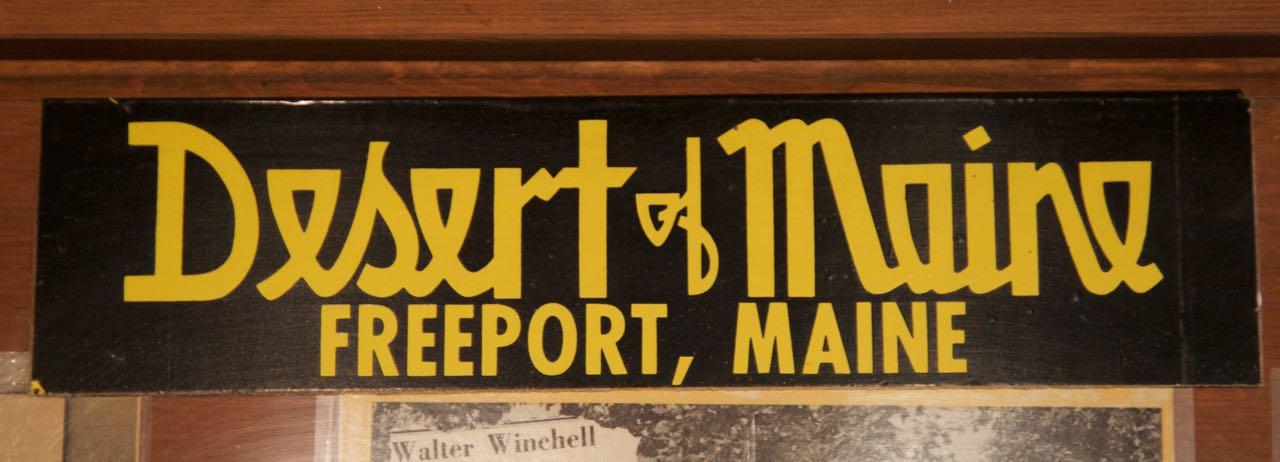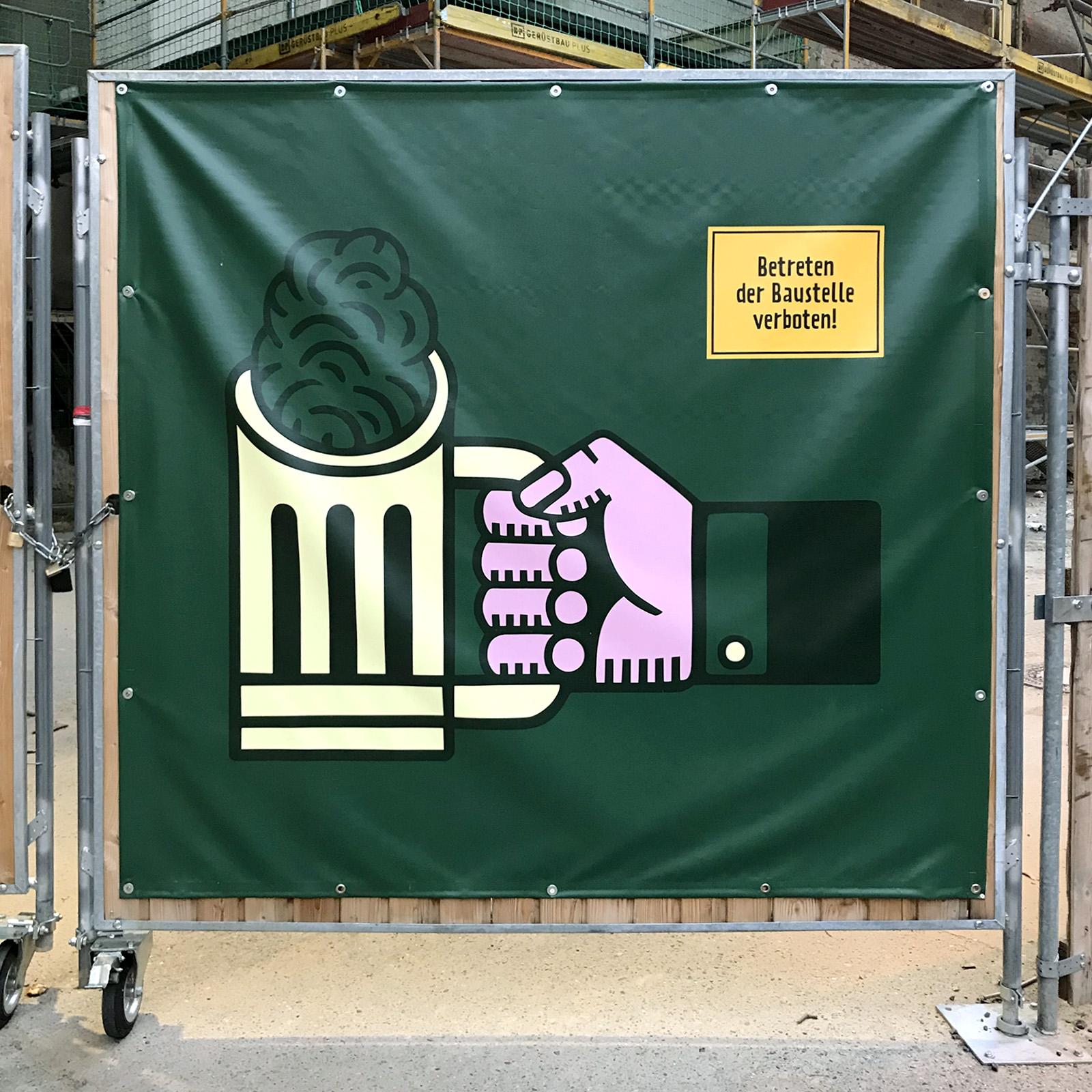
Hier also wieder etwas Schriftbezogenes. Das Schild ist zwar gemalt, also eher Lettering, aber ich meine ich hätte diese Schrift schon irgendwo gedruckt gesehen. Kennt sie jemand?
Zugegebenermaßen sieht die o-f-Verbindung schon nach einem Sütterlin a aus :nicken:
Da hätte sich der Drucker aber auch etwas mehr Mühe geben können … :-o